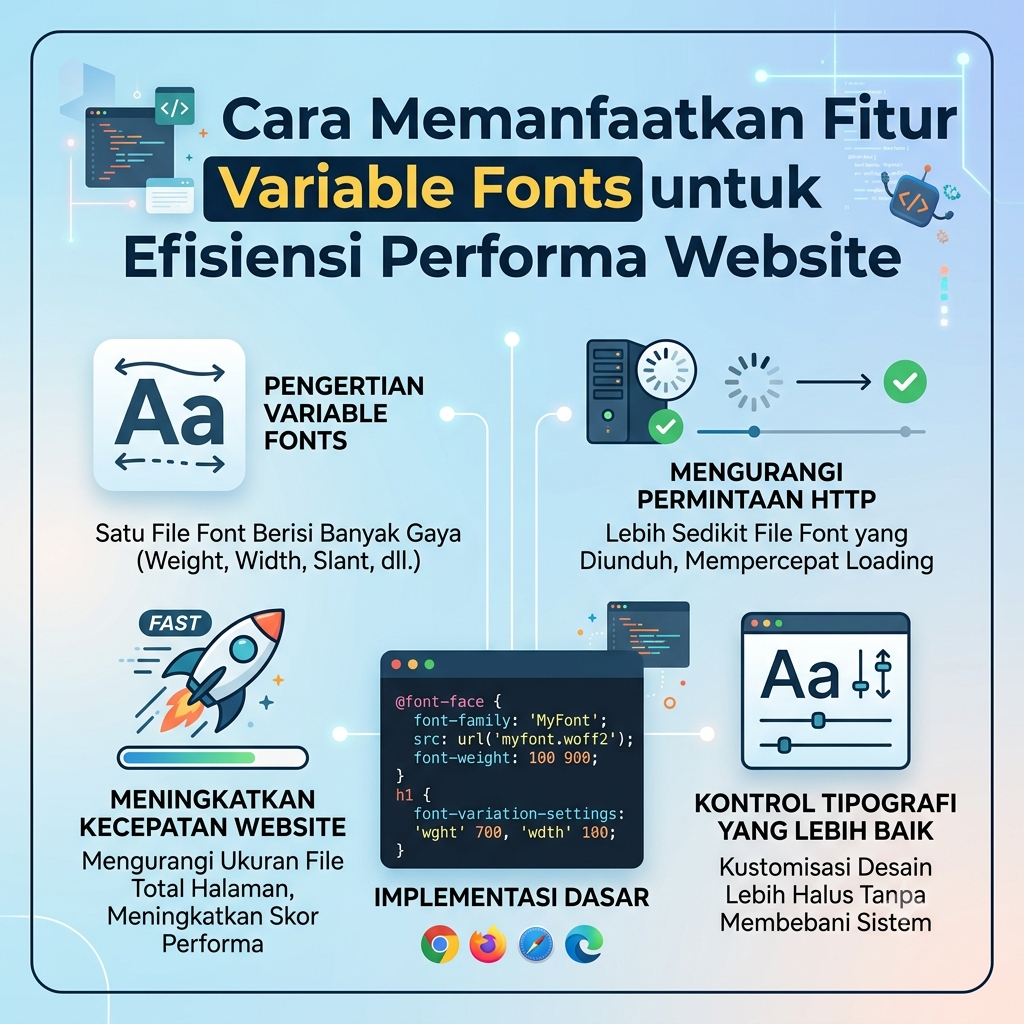
Nah, salah satu alasan kenapa website suka lemot adalah karena terlalu banyak file font yang harus di-download sama browser. Bayangin aja, lo mau pakai gaya Light, Regular, Bold, plus versi Italic-nya. Itu artinya browser harus ngunduh 4 sampai 8 file terpisah!
Untungnya, sekarang ada solusinya: Variable Fonts. Apaan tuh dan gimana cara manfaatinnya biar website lo makin ngebut? Yuk, kita bedah bareng-bareng!
Apa Sih Variable Fonts Itu? (Satu File Buat Semua Gaya!)
Gampangnya gini: Variable Fonts itu adalah teknologi font modern yang memungkinkan lo menyimpan beraneka ragam gaya font (seperti tingkat ketebalan/weight, kemiringan/italic, hingga lebar huruf/width) cuma dalam satu file tunggal.
Kalau pakai font konvensional (static fonts):
Kalau pakai Variable Fonts:
Keuntungan Variable Fonts buat Performa Website
HTTP Request Bikin Hemat: Browser cuma perlu minta 1 file ke server, bukan belasan file.
Ukuran File Lebih Kecil (Total Size): Meskipun 1 file variable font ukurannya sedikit lebih besar dari 1 file static, ukurannya jauh lebih ringan dibanding lo gabungin 4-5 file static fonts sekaligus.
Desain Lebih Fleksibel: Lo gak cuma terikat sama ukuran bold standar (misal 400 atau 700). Lo bisa atur ketebalan di angka berapa aja, contohnya
435atau620!
Cara Memanfaatkan Variable Fonts di Website Lo
Menerapkan variable fonts di coding-an CSS lo itu gampang banget, lho. Ikuti langkah-langkah simpel ini:
Cari & Unduh Variable Font
Lo bisa cari di platform gratisan kayak Google Fonts. Cari font yang punya label “Variable” (contohnya: Inter, Roboto Flex, atau Open Sans).
Panggil Font Menggunakan
@font-faceDi file CSS lo, panggil file variable font tersebut:
CSS@font-face { font-family: 'InterVariable'; src: url('Inter-Variable.woff2') format('woff2-variations'); font-weight: 100 900; /* Rentang ketebalan yang didukung */ font-display: swap; /* Biar teks tetap muncul saat loading */ } -
Gunakan Property
font-weightataufont-variation-settingsSekarang lo bebas ngatur ketebalan huruf sesuka hati pakai angka berapa aja:
CSSh1 { font-family: 'InterVariable', sans-serif; font-weight: 750; /* Kustom ketebalan tanpa batas! */ }
Komparasi: Static Fonts vs Variable Fonts
Biar kelihatan jelas bedanya, cek perbandingannya di tabel ini:
| Fitur / Parameter | Static Fonts (Cara Lama) | Variable Fonts (Cara Modern) |
| Jumlah File | Banyak (1 file per gaya) | Cukup 1 File |
| Beban Loading Server | Berat (Banyak HTTP Requests) | Ringan & Efisien |
| Fleksibilitas Gaya | Terbatas pada preset (400, 700, dll.) | Bebas & Responsif (Rentang 100 – 900) |
| Cocok Untuk | Desain simpel 1-2 gaya font | Website modern yang butuh banyak variasi gaya |